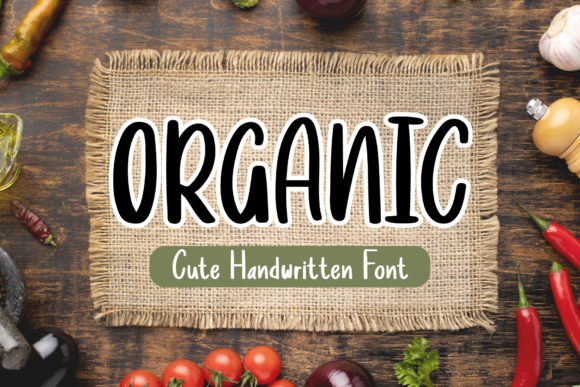
Organic
Encontrar los elementos de diseño adecuados puede ser un desafío, pero Organic ofrece una colección excepcional que eleva tu trabajo al instante.
Elaborado con precisión, Organic proporciona vectores limpios, tipografía suave y una licencia comercial para tu tranquilidad.
Ya sea que estés creando productos POD (impresión bajo demanda), invitaciones de boda o gráficos para redes sociales, Organic es una opción ideal.